Tìm được một font calligraphy thích hợp cho thiết kế của bạn có thể là một việc khó khăn và gian khổ. Một số font calligarphy thường quá nhiều chi tiết trang trí và cầu kỳ cho thiết kế đơn giản của bạn, trong khi một số khác lại quá đơn giản và hiện đại cho một thiết kế trang trọng.
Có nhiều cách sử dụng font calligraphy và chúng được kết hợp tốt nhất cùng với một font chữ giản dị để tạo nên sự cân bằng. Sử dụng chúng một cách tiết chế để thiết kế của bạn không bị quá lố hoặc phá vỡ quy tắc để xem mình có thể tạo ra được điều gì.
20 font calligraphy miễn phí dưới đây có thể sẽ đáp ứng đủ cho mọi yêu cầu của bạn, từ những nét cong lãng mạn và nữ tính cho đến những font in đậm và nam tính sẽ mang cá tính vào trong thiết kế của bạn.
1. Balqis
By Ann Moore
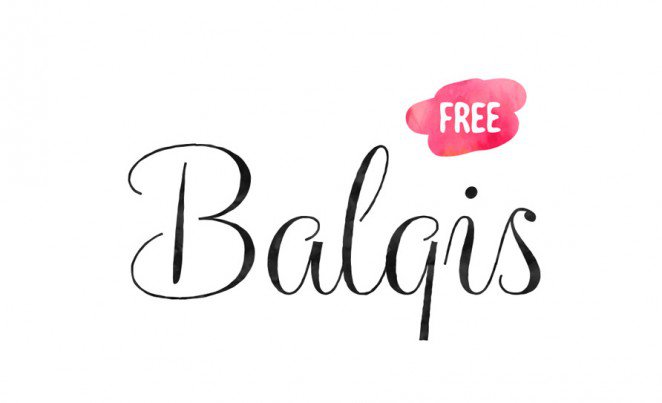
2. Blackjack
By: Typadelic
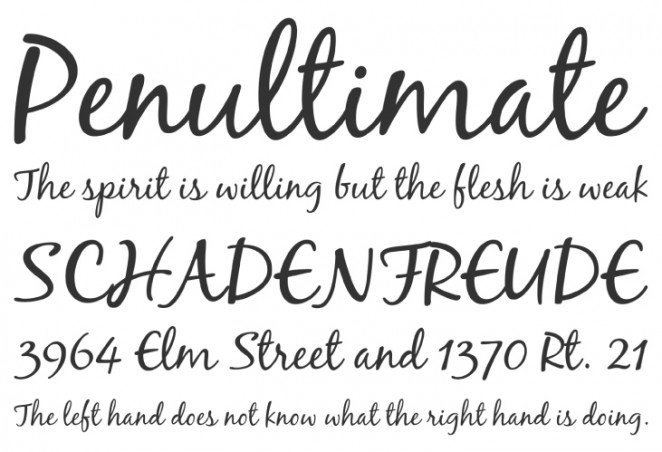
3. Blenda
By: Seniors Studio
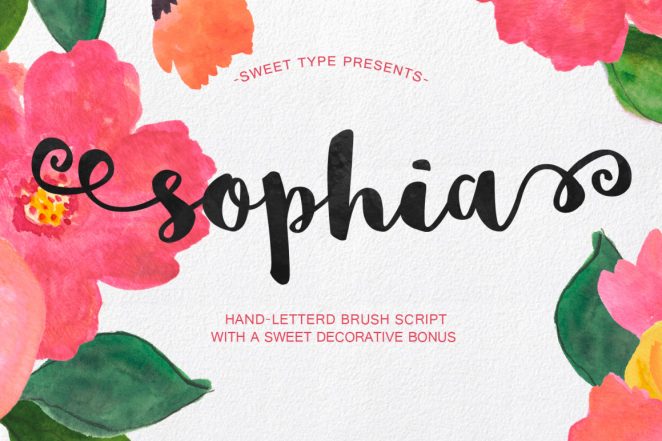
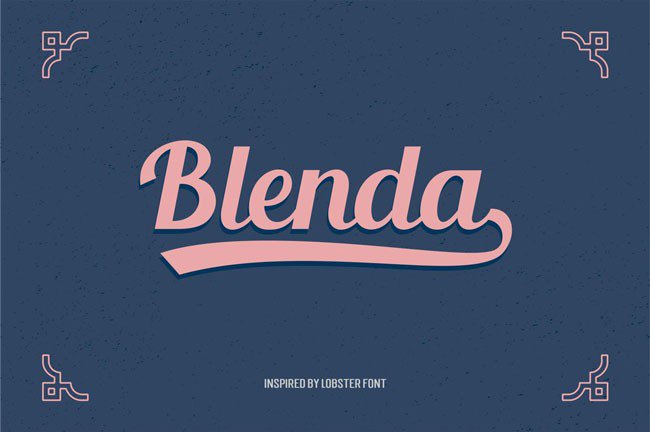
4. Sophia
By: Emily Spadoni
5. Bukhari Script
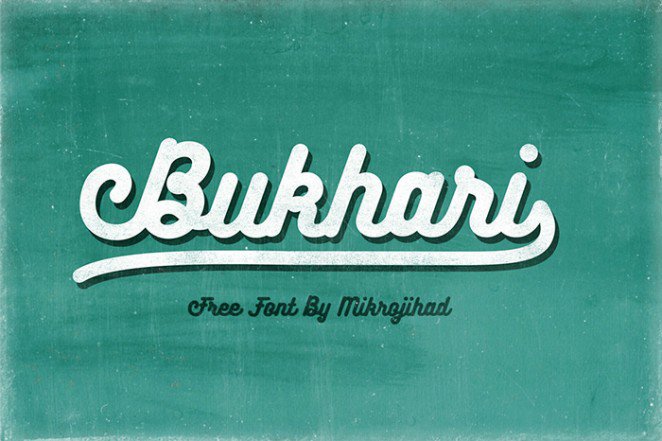
6. Cursif
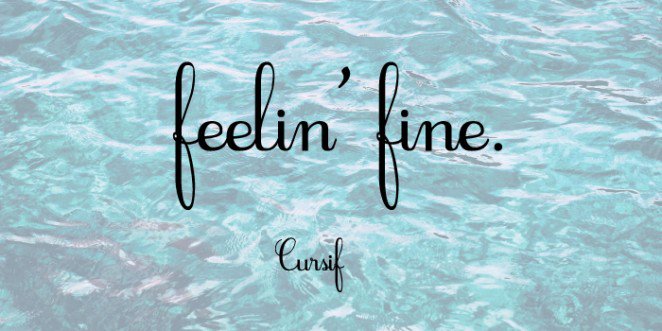
7. Dancing Script:
By: Impallari Type
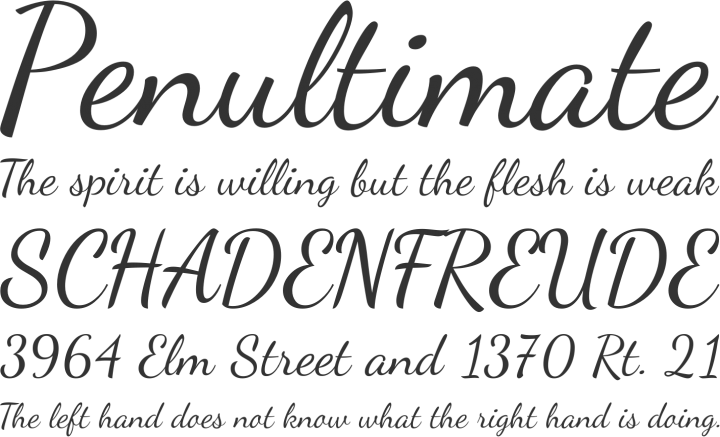
8. Fabfelt Script
By: Fabien Despinoy
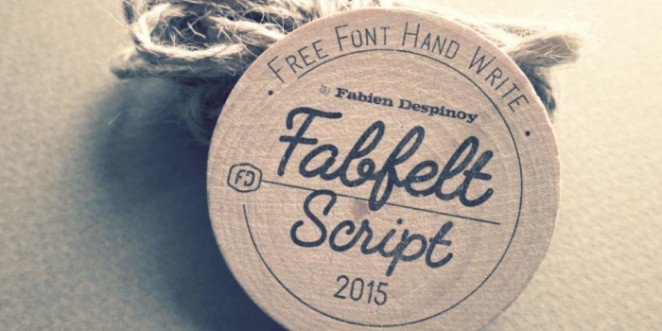
9. Good Vibes
By: Peter Olexa
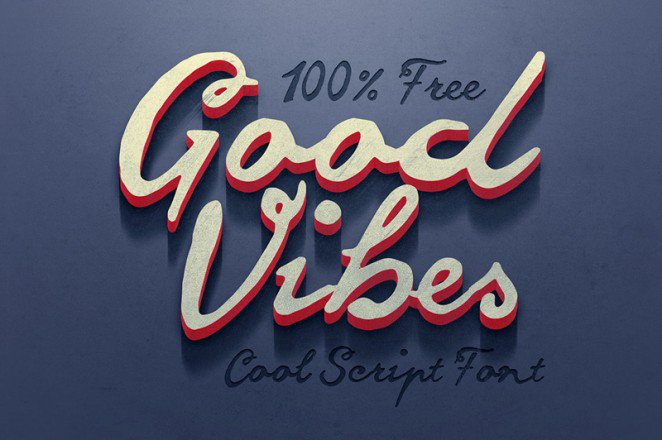
10. Grand Hotel
By: Astigmatic
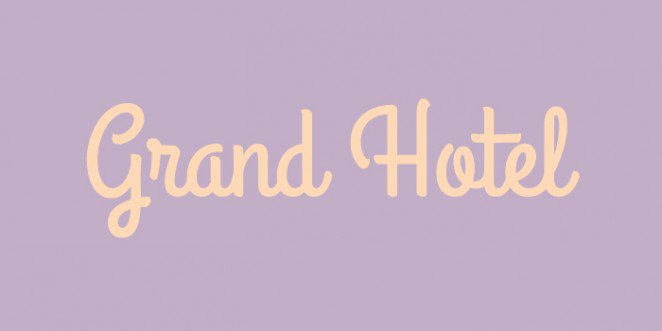
11. Learning Curve Pro
By: Blue Vinyl Fonts
12. Little Days
By: Blue Vinyl Fonts
13. Lobster:
By: Impallari Type
14. Masana Script:
By: Mario Arturo
15. Nickainley
By: Seniors Studio
16. Scramento:
By: Astigmatic One Eye Typographic Institute
17. Qwigley Regular
By: Robert E. Leuschke
18. Oleo Script:
By: Soytutype Fonts
19. Pacifio:
By: Vernon Adams
20. Satisfy
By: Font Diner